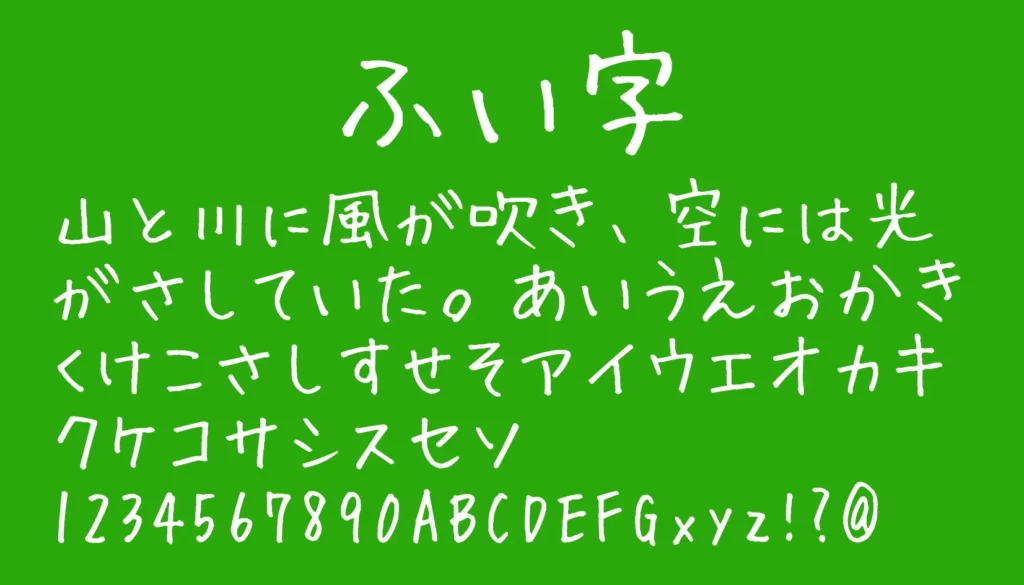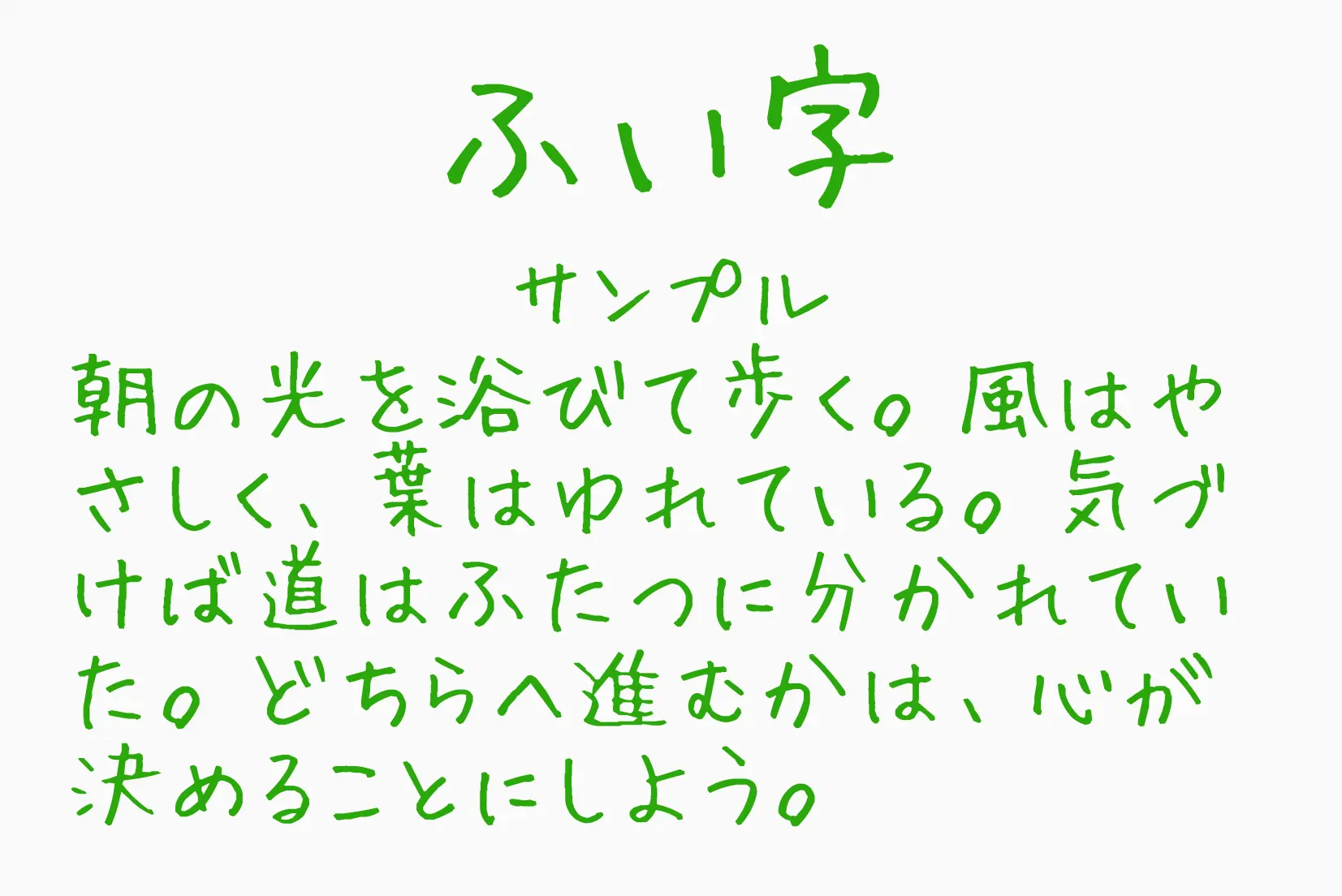
ノートやメモにさらっと書いたような自然な手書き感が魅力のフリーフォントです。細めの線で構成されているため圧迫感がなく、やさしく親しみやすい雰囲気を演出できます。かわいらしさはありつつもクセが強すぎないため、ブログのアイキャッチやSNS投稿、手紙風デザイン、動画テロップなど幅広い用途で活躍。ひらがな・カタカナだけでなく漢字も豊富に収録されており、実用性の高さも魅力のひとつです。
ふい字